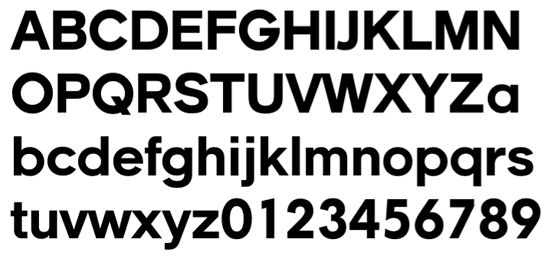
Une fois de plus le monde de la création des logos affiche son drapeau en berne. Et nous sommes à jour J moins quelquechose pour l’annonce de la nouvelle marque d’Air France. Au secours.
Oui mais!!! qui c’est ce gars qui ose, critiquer le travail des autres graphistes-designers? Alors je vous rassure tout de suite, ce n’est pas mes confrères que je critique mais plutôt le système qui fait qu’on accouche de ce genre de com-promis.
Voici ci-dessous l’ancienne marque de la célèbre firme automobile qui fit tant de chemin depuis la croisière jaune.
Voici la définition que donne Wikipedia de l’A.D.N.
L’acide désoxyribonucléique ou ADN [1] est une molécule, retrouvée dans toutes les cellules vivantes, qui renferme l’ensemble des informations nécessaires au développement et au fonctionnement d’un organisme. L’ADN est aussi le support de l’hérédité car il est transmis lors de la reproduction, de manière intégrale ou non. Il porte donc l’information génétique, il constitue le génome des êtres vivants.
On comprend donc tout de suite que l’expression ADN d’une marque est une de ces néologismes qui autorisent tout et son contraire. Car en matière de marque «l’hérédité et l’ensemble des informations nécessaires…» relève plus de l’irrationel et de l’émotionnel que de la formule moléculaire quasi mathématique.
Alphabet dessiné par l’Agence Delpire en charge du budget Citroën jusqu’aux années 1976. Une Europe (style Futura), aux jambages très courts augurant des principes qui ont fait le succès des caractères ITC à partir des années 70.
La traction avant dans la Main au Collet d’Alfred Hitchcock: «nooon des poulets…» réplique des policiers alors qu’ils venaient de sortir de la route à cause d’une colonie de poulets qui traversaient la corniche de Monaco. «Des poulets vous-dis-je»
En vérité les voitures Citroën ont toujours bénéficié d’un design aux formes plutôt arrondies. Ce faisant les chevrons aux angles aigus venaient en contrepoint de la douceur des voitures et «vivaient» parfaitement bien le paradoxe de cette dissonance.
Le nouveau design du logo prétendrait donc rappeler l’arrondi des formes automobiles comme si cette dissonance n’avait plus lieu d’être pour une obscure raison philosophique qui interdirait toute diversité et toute assemblage des différences ethniques. Les blonds ne pourraient plus se marier avec des brunes, les grands avec des petites. Permettez-moi de douter de ce formatage de bas niveau voire même de douter de mes doutes. Parce qu’on atteint en même temps la limite de l’intelligence humaine.
Un chevron, comme un guillemet posé verticalement, reste un chevron. Et l’aspect anguleux de la forme est essentielle à son identification. Si vous examinez les nouveau chevrons, et vous oubliez un instant la connexion chevron=Citroën, vous voyez quoi? Deux boomerangs superposés. Les boomerangs ont précisément cette forme arrondie qui leur permet de voyager dans l’espace et revenir à leur point de départ. Alors oui, pourquoi pas. Je prends ma voiture, je fais un petit tour et reviens à mon point de départ. Sauf que nous ne sommes pas sûrs du tout de cette sémantique schémanitoire (j’adore inventer des mots :-).
Et par delà cette pseudo modernisation style Citroën 2.0 qui correspond bien à l’air du temps et au désir d’un constructeur d’investir le champ d’internet (où l’on se déplace virtuellement) pour pallier à la baisse tendancielle des fréquentations de la télé, on peut se demander si les décideurs de Citroën ne sont pas en train de «péter un plomb» croyant pouvoir pallier à la baisse des ventes automobiles par un relookage de leur logotype. Je ne dis pas que la création de marques, le relifting des labels est totalement inutile, au contraire. Mais autant j’ai pu apprécier la modernisation du logotype-bloc marque de Renault, autant j’ai le sentiment que Citroën donne dans une stratégie-panique où elle espère limiter la casse par un nettoyage parfaitement superfétatoire et tendancieuse qui sera démodé avant même d’avoir eu le temps de dire ouf.
Quant au dessin de l’alphabet, je n’ai qu’un mot à rajouter: ce n’est pas sérieux. Fantaisie à peine bonne pour être donnée en shareware sur Dafont, c’est vraiment faire injure à la qualité et aux professionnalisme de nos excellents typographes qui auraient pu tous accoucher d’un alphabet autrement plus sérieux, moins douloureux, que cette création hasardeuse qui ne rend pas compte de la culture ni du sérieux d’une marque presque centenaire. Mais je peux me tromper et si vous le pensez, n’hésitez pas à argumenter. :-)
1) Heureusement que Ferrari ne change pas de logo chaque fois que la marque perd une course de Formule 1
2) que la marque Ferrari ne rend absolument pas compte de l’ADN d’un label très haut de gamme où une California 1962 a été vendue aux enchères 15.000.000 d’euros l’année dernière à Londres à un présentateur de la télé BBC.